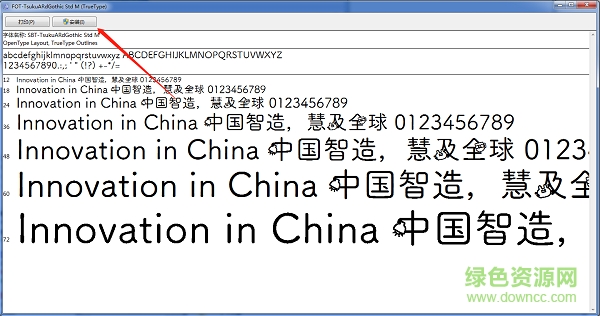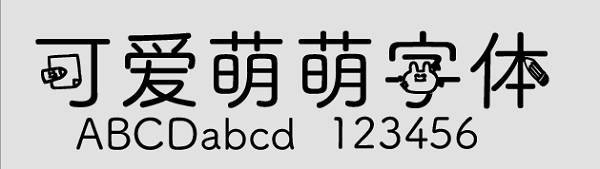
可愛(ài)萌萌字體是一款以呆萌可愛(ài)為主要設(shè)計(jì)題材的字體,字體整體看起來(lái)比較的圓潤(rùn),在字體中添加了各種不同的小道具,給用戶更多可愛(ài)的感覺(jué),適用于多種地方,喜歡就來(lái)綠色資源網(wǎng)下載吧!
可愛(ài)萌萌字體是一款非??蓯?ài)的電腦中文字體,可以一鍵安裝到電腦中,擁有可愛(ài)、萌系、卡通等字體風(fēng)格!
將漢字與各種卡通圖案融合,并且完全不會(huì)影響漢字識(shí)別度,讓字體擁有更強(qiáng)的顯示效果!
是廣告設(shè)計(jì)、印刷品制作、雜志等常用卡通字體!